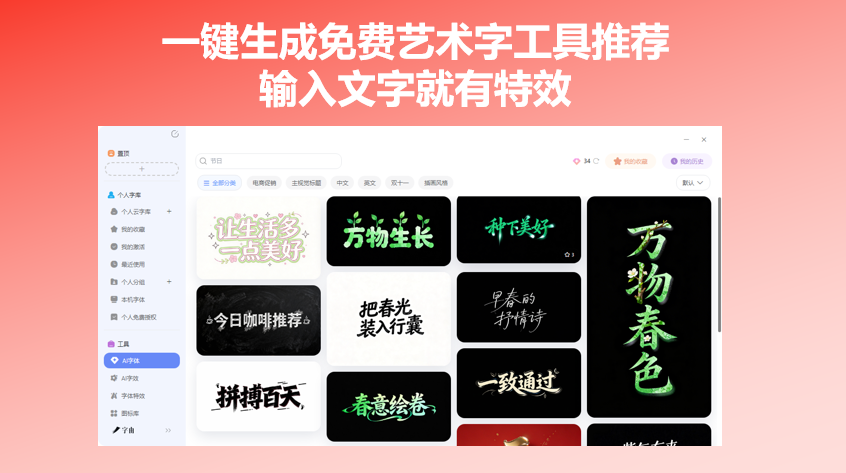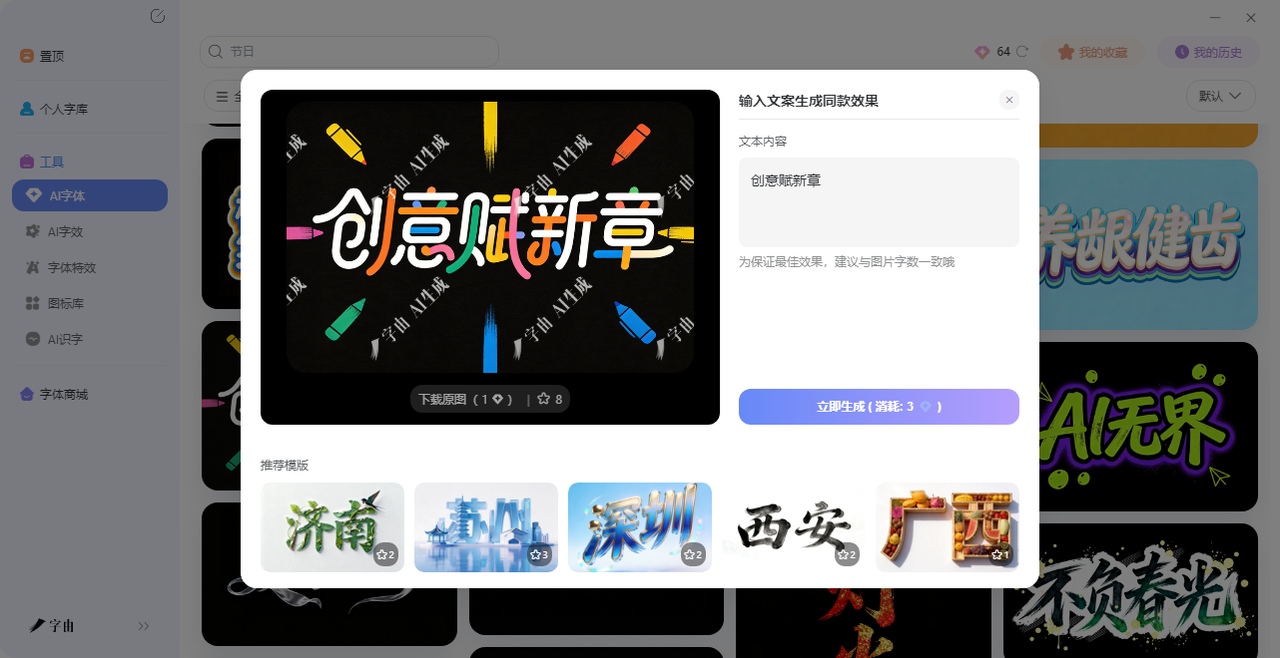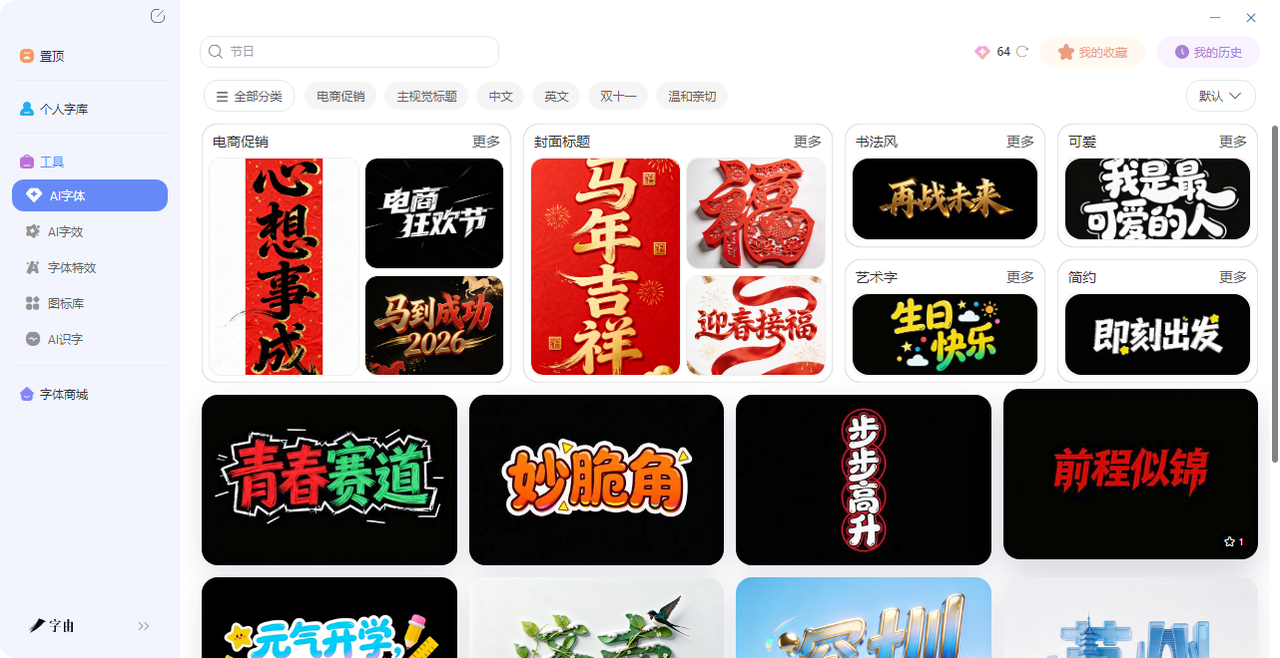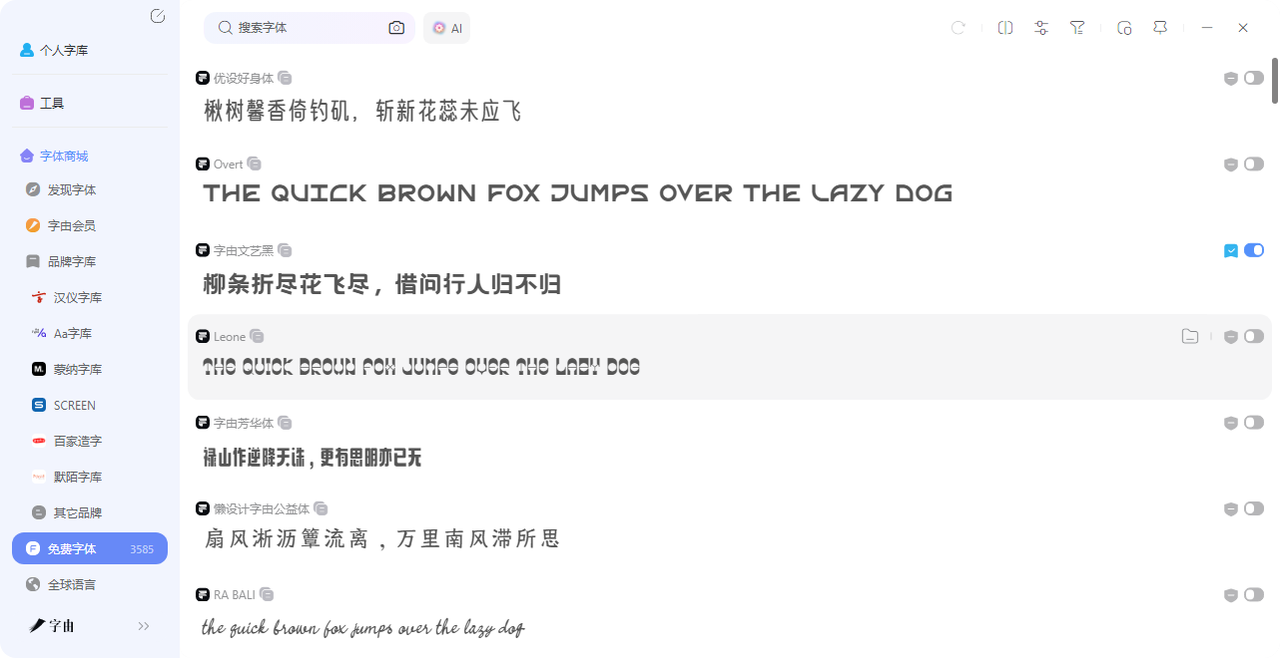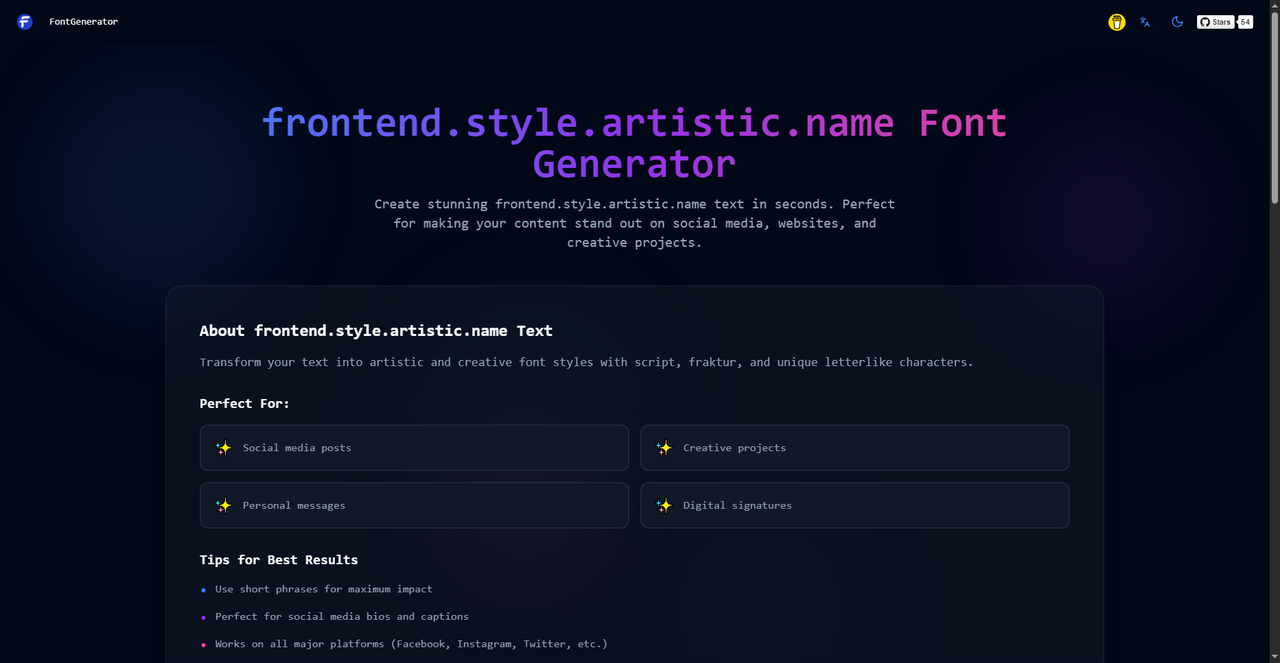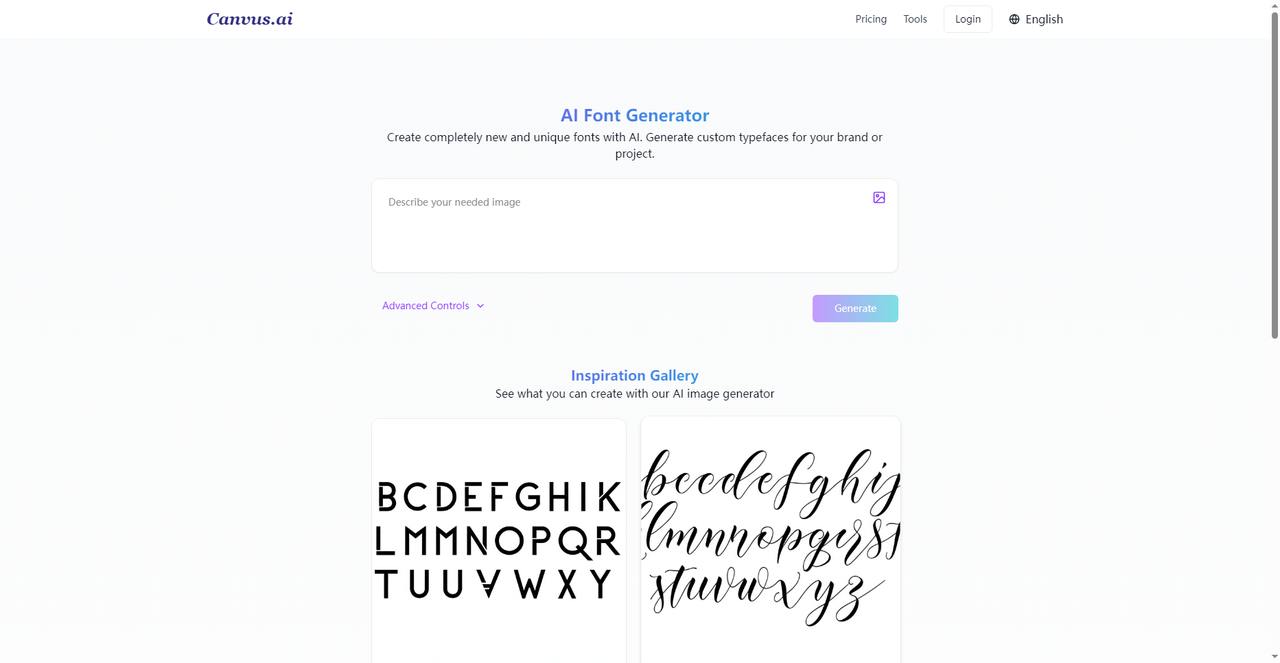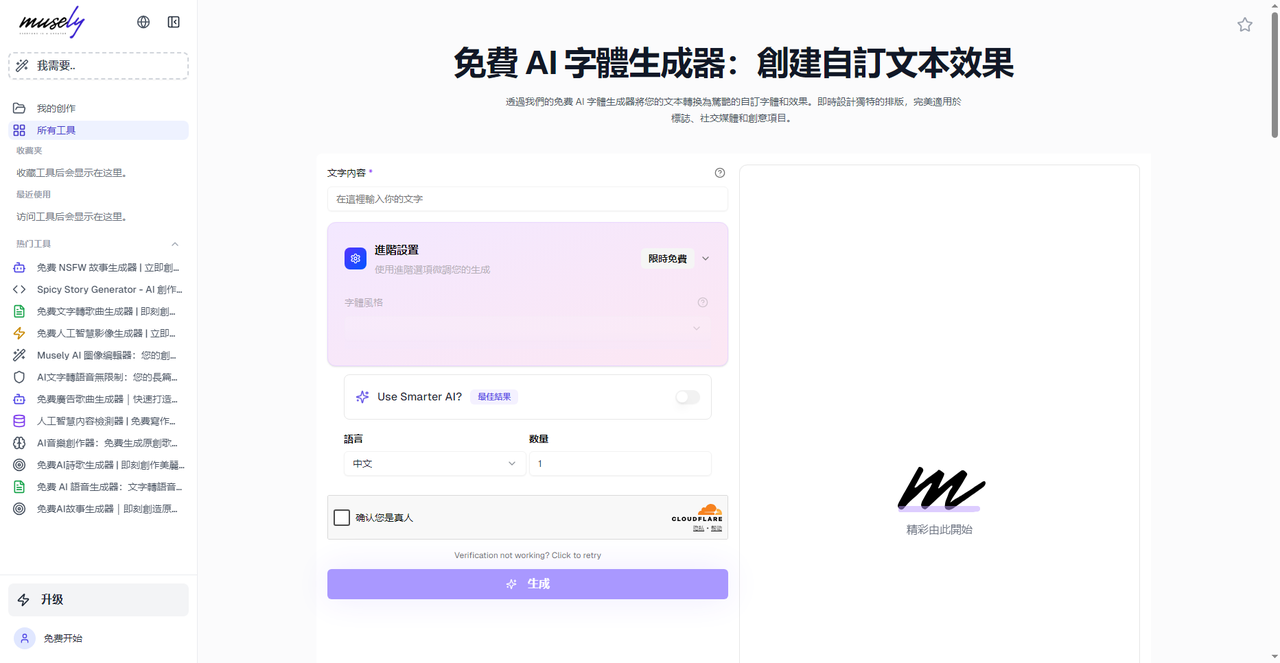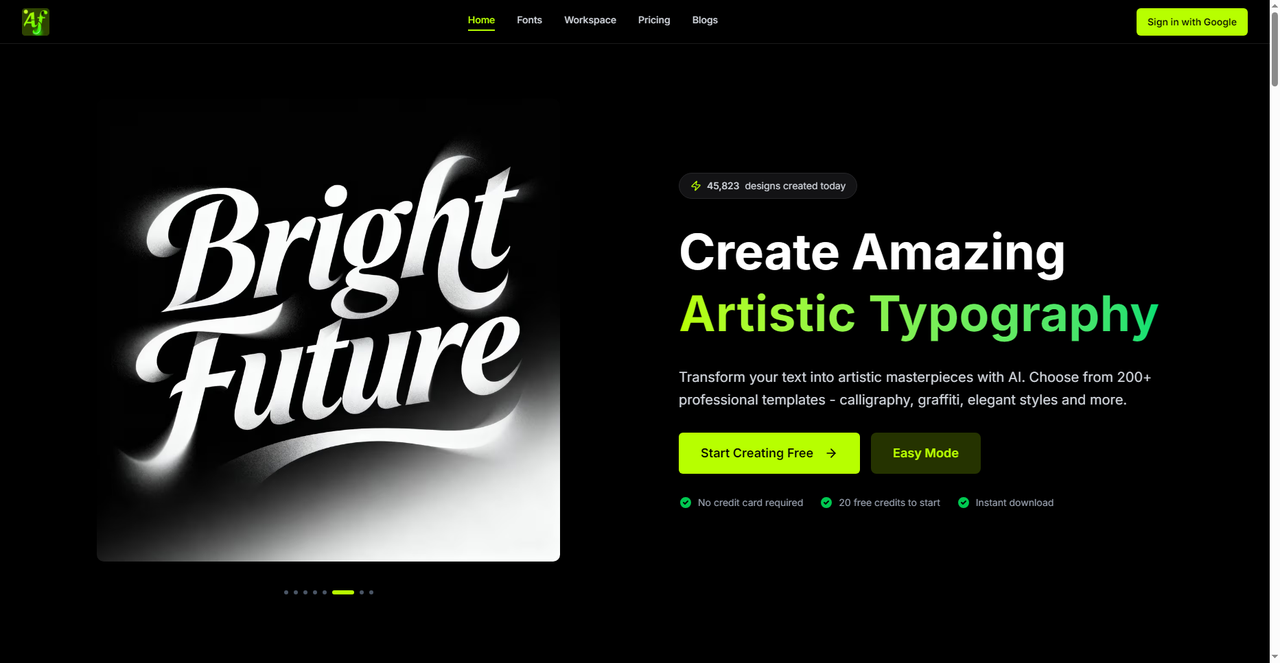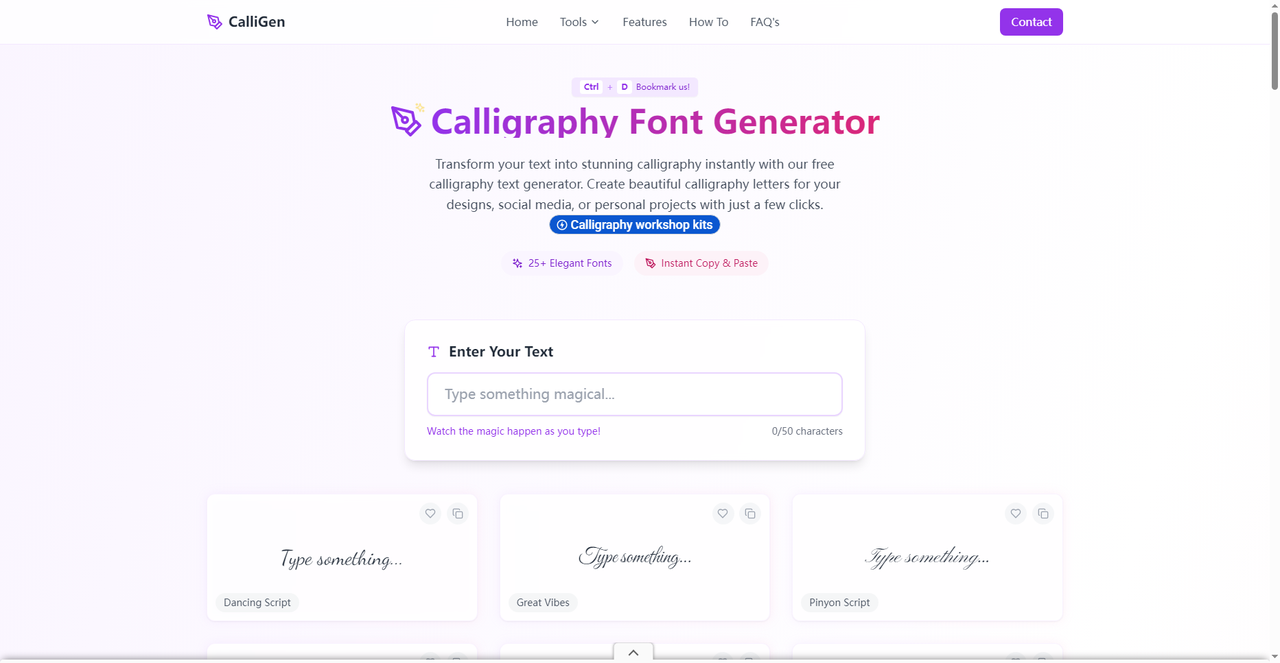
以前想做艺术字,得先会PS,得懂图层样式,得知道怎么调光影。现在不用了。打开网页,输入文字,选个风格,点一下,几十秒就有结果。今天就把我私藏的6 个免费艺术字生成工具分享出来,从国产神器字由到国外AI平台,每个都能让你输入文字就拿到带特效的艺术字。需要的直接收藏。
很多人用字由,只看到它字体多,却不知道它的“AI字体”功能,本身就是一款超级好用的艺术字生成器。你不需要下载任何字体,也不用装软件,打开网页就能用。接下来我会给大家详细介绍一下如何使用字由的AI字体功能。
你只需要打开字由官网,找到【AI字体】。在搜索框里输入你想要的效果,比如“霓虹”“金属”“国潮”“手写”“3D”,系统会筛出对应的模板。每个模板都是现成的设计——带特效、带配色、带背景,你不需要自己调任何参数。
然后再选一个顺眼的模板,点击“做同款”,把模板里的文字换成你的标题(最好和模板字数一样)。点击“立即生成”,等20-30秒,就能拿到一张高清艺术字图片。下载时有两个选项:带背景的可以直接用,透明背景的更方便后期排版。直接保存PNG格式,就能拖进PS、Canva、剪映里用。不需要抠图,不需要调色。
最主要的是字由的AI字体模板库非常丰富,按场景分好了类:电商促销、主视觉标题、节日、国潮、科技、手写……每个分类下都有几十种风格。比如:
• 霓虹灯管:带玻璃管质感的霓虹字,适合音乐海报、酒吧招牌、夜店活动
• 金属质感:拉丝不锈钢、铬金属高光、古铜做旧,适合科技产品、工业风设计
• 国潮书法:水墨晕染、毛笔飞白,适合国风海报、传统文化内容
• 水彩晕染:边缘模糊、颜料渗开的效果,适合文艺类封面、手账标题
• 3D立体:带厚度和透视的立体字,适合游戏标题、品牌Logo
• 节日喜庆:大红底色、金色描边、灯笼装饰,适合春节、促销活动
如果你不想要特效,只是想用现成的艺术字体,字由的免费商用字体库里也有大量选择。字体都可以在字由的“全部字体”里找到。我会推荐这几个常用的字体:
• 字由文艺黑:既有黑体的稳重,又带一点手写感。做海报主标题、品牌Logo,或者需要“正式但不死板”的感觉时,用它很对味。
• 优设标题黑:方正有力,做电商海报、促销活动的标题,视觉冲击力强。
• 字由芳华体:温柔手写风,做文艺类封面、情感类海报,很出片。
• 点字浅夏体:清新手写,做旅行vlog封面、生活记录类标题,很加分。
• 沐瑶软笔手写:圆润治愈,做亲子类海报、手账内容,暖暖的。
• 北窗墨刃:书法感强,做国风设计、电影海报,很有味道。
2、Font Generator
这个网站是一个花式字体生成器。输入文字后,下面会列出几十种不同风格的字体预览:Script、Bold Script、Fraktur、Bold Fraktur、Double Struck、Bubbly、Vai Letterlike、Black Bubble……每种风格都有“Copy”按钮,点一下就能复制到剪贴板,直接去微信、微博、Instagram粘贴。它还有直接分享到社交媒体的按钮,很方便。适合做社交媒体文案、个人简介、评论区签名。完全免费,不用注册。
3、AI Font Generator
这个网站不是让你选模板,而是用AI根据你的描述生成全新的字体。在输入框里写一段描述,比如“a futuristic sci-fi font”,AI会生成一套完整的字符样本图片。你可以反复调整描述,直到满意为止。生成的不是可下载的字体文件,而是字符集的图片,可以用作设计灵感或参考。适合想要独一无二字体的设计师,或者做品牌定制字体时找方向。
4、免费 AI 字体生成器
这是一个中文的AI字体生成器,支持中文输入。界面简洁,输入文字,选择语言(中文/英文),点击生成,AI会输出带艺术效果的文字。它需要过验证码(可能是防机器人机制),但生成效果还不错。如果你想要中文艺术字,又不想用字由,这个可以作为备选。
5、ArtFont
这个网站提供了200多种专业艺术字模板,分类很细:Calligraphy(传统书法)、Street Art(涂鸦)、Neon Glow(霓虹)、Elegant Minimal(简约高级)、Retro(复古)等。每个模板都有使用次数和评分,方便挑热门的。注册就有20 个免费额度,无需信用卡,生成后可以即时下载。如果你想要AI推荐、模板多、更新快,这里很合适。
6、CalliGen
这个网站专门做书法风格的花式字体。输入文字后,下方会展示多种书法字体的预览,比如Dancing Script、Great Vibes、Pinyon Script、Alex Brush、Tangerine、Parisienne等。每个字体旁边都有“Copy”按钮,点一下就能复制,直接粘贴到社交平台或文档里。适合做签名、婚礼请柬、英文书法风格的文案。完全免费,无需注册。